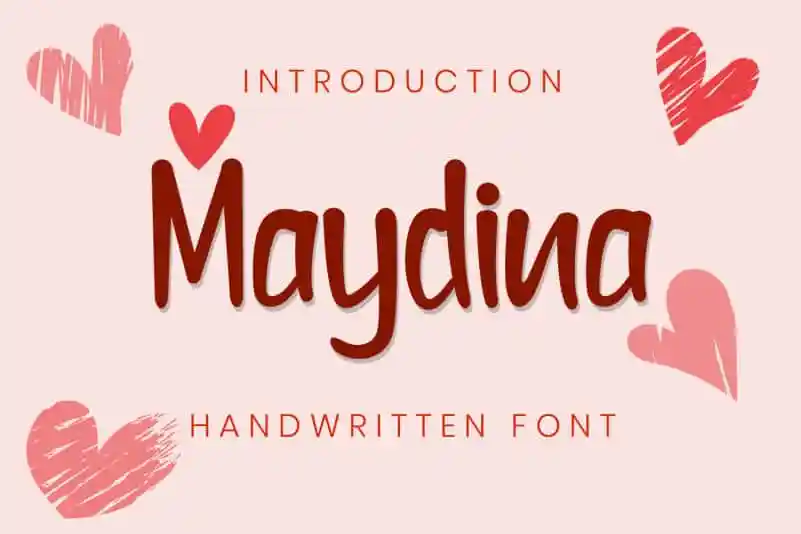
Maydina Handwritten Font
A Maydina Handwritten Font é uma fonte escrita a mão com um toque suave e quirk. Ela combina características naturais e únicas que tornam-se ideais para uma ampla variedade de design, limitadas apenas pela criatividade do seu designer. A planetz studio criou esta fonte com um estilo único que traz vida aos seus trabalhos digitais, fazendo a Maydina ser perfeita para aplicação em logotipos, identidades visuais e até mesmo texturas de design gráfico. Essa fonte não apenas é uma escolha atraente para qualquer projeto pessoal ou profissional, mas também um elemento que pode dar ao seu trabalho um toque personalizado e único. Não importa o tipo de design que você está criando com Maydina Handwritten Font, ela certamente ajudará a transformar sua ideia em uma peça única e memorável.